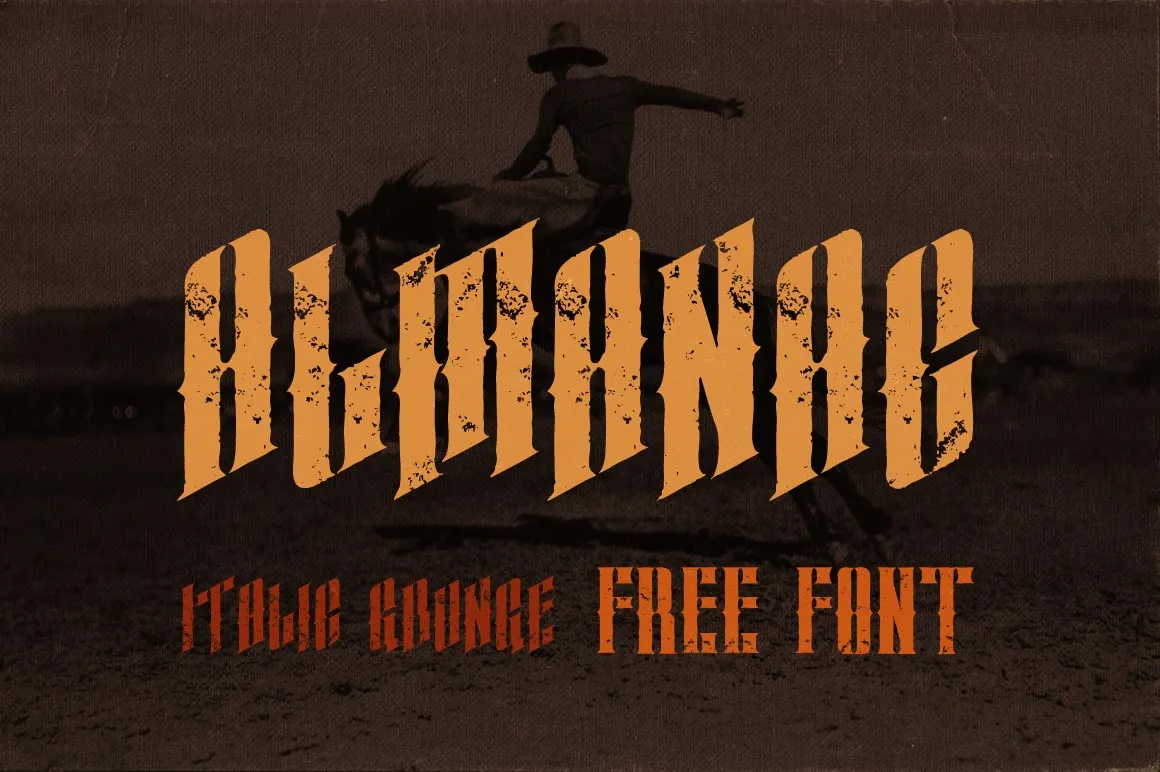
Almanac Italic Grunge Font – Download Grátis
A fonte “Almanac Italic Grunge” é uma escolha excepcional para projetos que desejam adicionar um toque vintage e moderno à sua designografia. Desenvolvida pela Jumbo Design, esta fonte grunge tem o charme atraente de um estilo retro, combinado com as linhas mais suaves da tipografia italica. Perfeito para aqueles projetos em que você quer incorporar um aspecto vintage e casual sem perder uma linha de qualidade e facilidade de uso. Desenvolvida pelo designer Hamilton, esta fonte oferece uma versão grunge com certa liberdade criativa para expressar texturas e sentimentos nostálgicos. É perfeita para criar designs que remetem à era 80s ou 90s, seja em revistas vintage, posters, cartões de aniversário, design editorial ou até mesmo em artes digitais inspiradas nos anos 70 e 80. Experimente a Almanac Italic Grunge e sinta-se encantado por explorar novos caminhos para o seu trabalho gráfico.